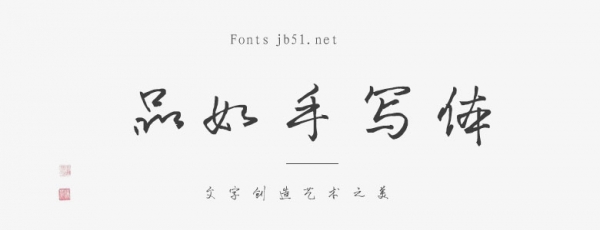
這些年下來(lái),許多字體都開始收版權(quán)費(fèi),十分苦惱,自己是個(gè)書法愛(ài)好者,索性寫一套自己的字庫(kù),想到就去做了,然后,歷時(shí)半年時(shí)間,利用業(yè)余時(shí)間,寫了這套字庫(kù),她的名字叫做【品如手寫體】
作者林芳檉,品如設(shè)計(jì)創(chuàng)意總監(jiān) 淘寶裝修市場(chǎng)專屬講師。曾任職于國(guó)際知名4A廣告公司奧美,服務(wù)過(guò)奔馳、三菱、網(wǎng)龍、中國(guó)移動(dòng)等知名客戶。受阿里巴巴邀請(qǐng)參與撰寫智庫(kù)新書《全網(wǎng)誠(chéng)信通》。